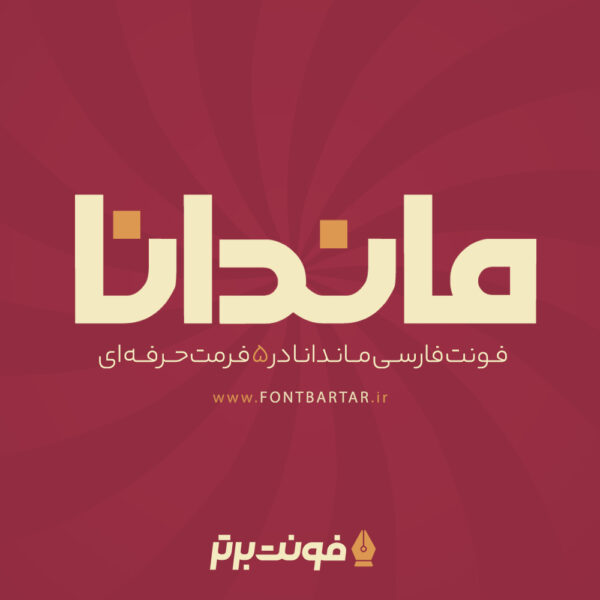
فونت ماندانا
Mandana Font
درود بر شما کاربران گرامی و طراحان ، “فونت ماندانا ” یک تایپ فیس هندسی و تزئینی می باشد که توسط طراحان فونت برتر پس از چند مرحله تغییرات در ضخامت، فرم حروف و نقطه‌ها با ظرافت خاصی در یک وزن بولد طراحی و به فونت تبدیل شده است.
فونت ماندانا دارای تمامی کاراکترهای زبان فارسی می‌باشد و قابل استفاده در متون کوتاه مثل عناوین کتاب، فضای پوستر و کارت‌ویزیت، تراکت، طراحی لوگو، تبلیغات محیطی و تابلوسازی اعم از: چنلیوم، حروف برجسته و اسلاید‌های اینستاگرام و کلا هر موضوعی مناسب است.
فونت ماندانا دارای چند وزن است؟
• فونت فارسی ماندانا در یک وزن می باشد.
فونت ماندانا از چه زبان هایی پشتیبانی می کند؟
• از فارسی پشتیبانی می کند.
حروف جایگزین فونت ماندانا